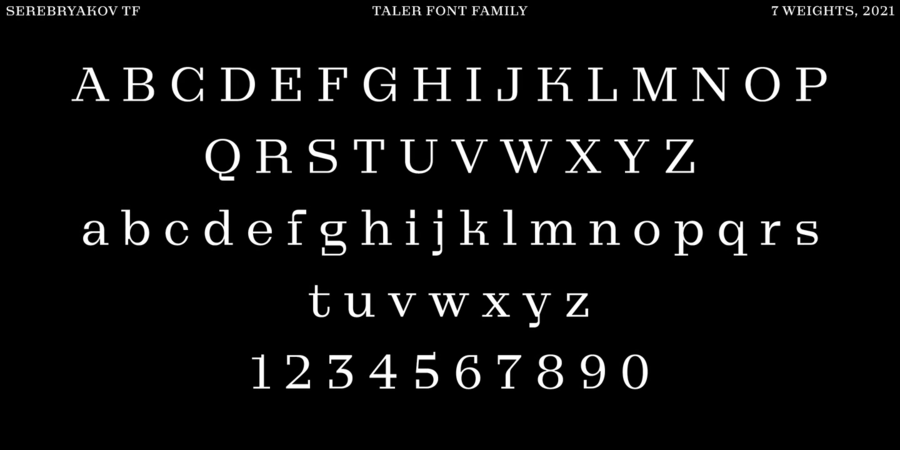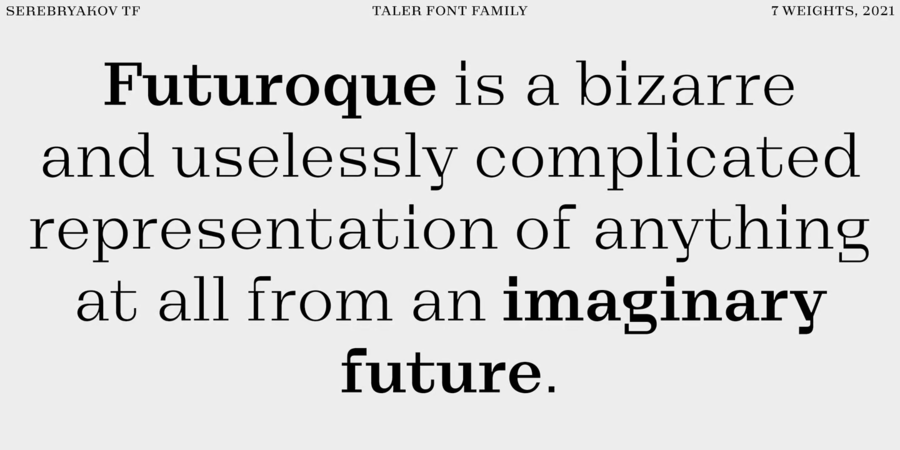
Taler (7 шрифтів)
Талер – це сучасна антиква у семи накресленнях. Гарнітура була задумана як доповнення до гротеску Nekst. У процесі розробки з'ясувалося, що виходить зовсім інший шрифт. Прямокутні, трохи подовжені зарубки, пластична жорсткість та поєднання різних стилів роблять Taler справжнім представником сучасності. Він призначений для акциденції та для основного тексту, водночас старомодний та сучасний, грубий та елегантний – всі ці якості присутні у шрифті одночасно. Його головна особливість – двоїстість. Шрифт розробив Денис Серебряков у 2021 році.
Асоціації з сімейством шрифтів TalerОсобистість і характер гарнітури:
точний, рівний, статичний, штучний, інженерний, міський, креслярський, сучасний, тонкий, дротяний, легкий, прохолодний, прозорий, модний, худий, дивний, цікавий, самобутній, оригінальний, характерний, технічний, гострий, твердий, впевнений, сталевий, машинний, дорогий, розкішний, багатий, діловий, розумний, освічений, якісний, культурний, добірний, знаменитий, різкий, світський, дзвінкий, космополітичний, логічний, надійний, урбаністичний, чіткий, стабільний, серйозний, переконливий, залізний, стійкий, індустріальний, техногенний, важкий, авторитетний, значний, мужній, сильний, важливий, монументальний, суворий, крутий, амбітний, практичний, міцний, формальний, солідний, самостійний, відповідальний, добротний, архітектурний, претензійний, яскравий, виразний, пафосний, помітний, урочистий, видовищний, гордий, грубий, прямокутний, жорсткий, потужний, кондовий
дизайн, мода, архітектура, Місто, технології, урбаністика, музей, годинник, преміум, розкіш, костюм, люкс, інтер'єр, хімія, прилад, інженер, наука, техніка, верстат, інструмент, промисловість, ремонт, взуття, меблі, сейф, архітектор, блокбастер, бойовик, екшен, зореліт, одяг, бутік, правосуддя, влада, Трофей, нагорода, карти, банкнота, гроші, краватка, фінанси, вечір Гарнітура має ознаки стилів: